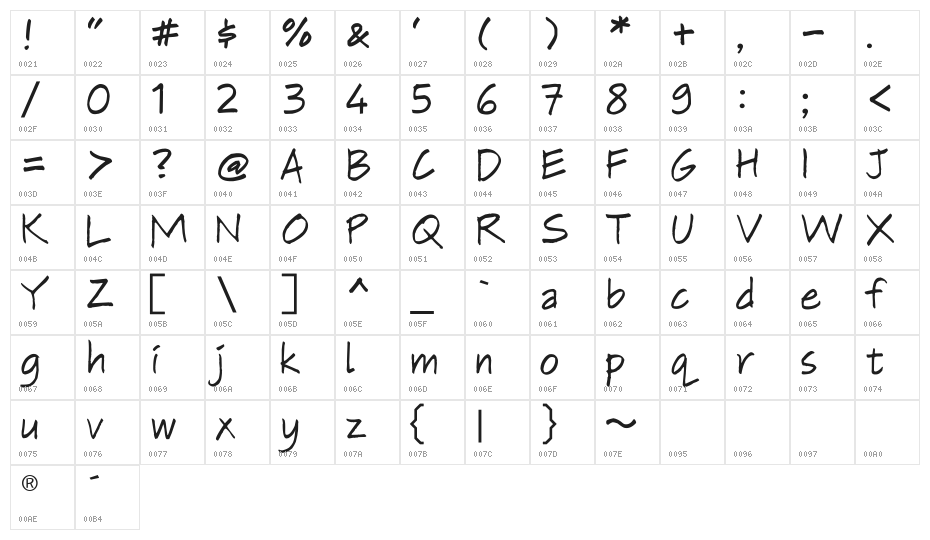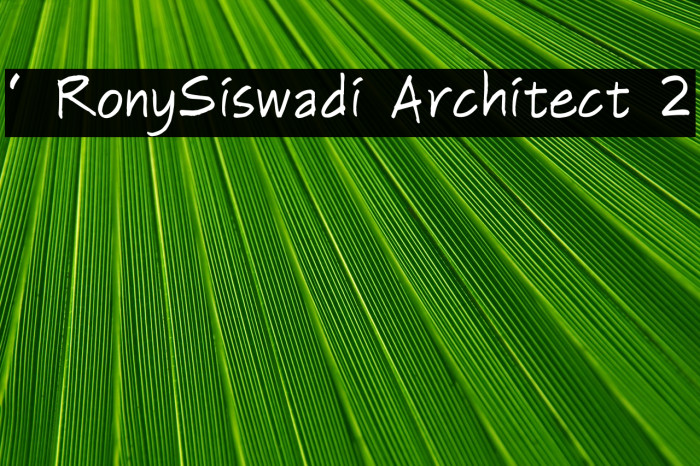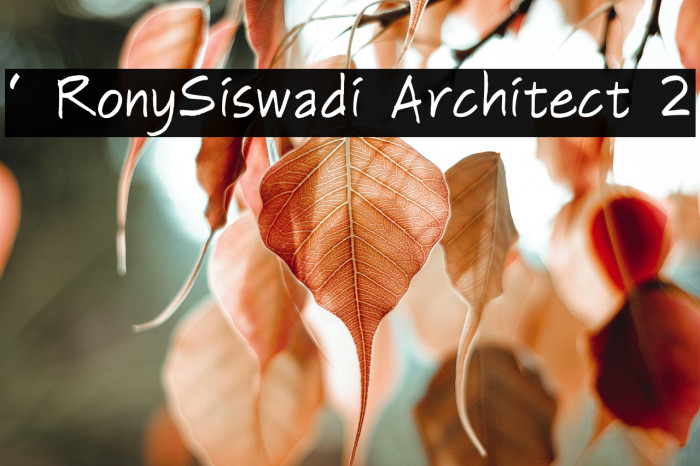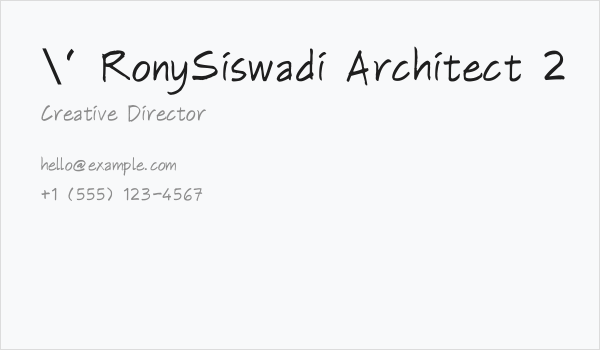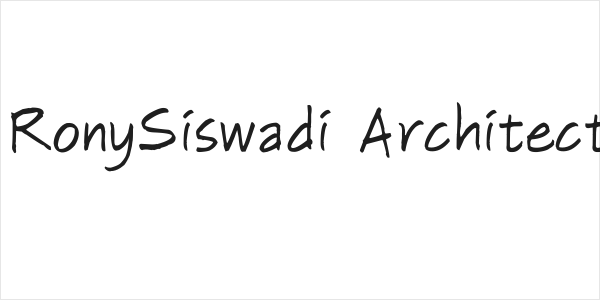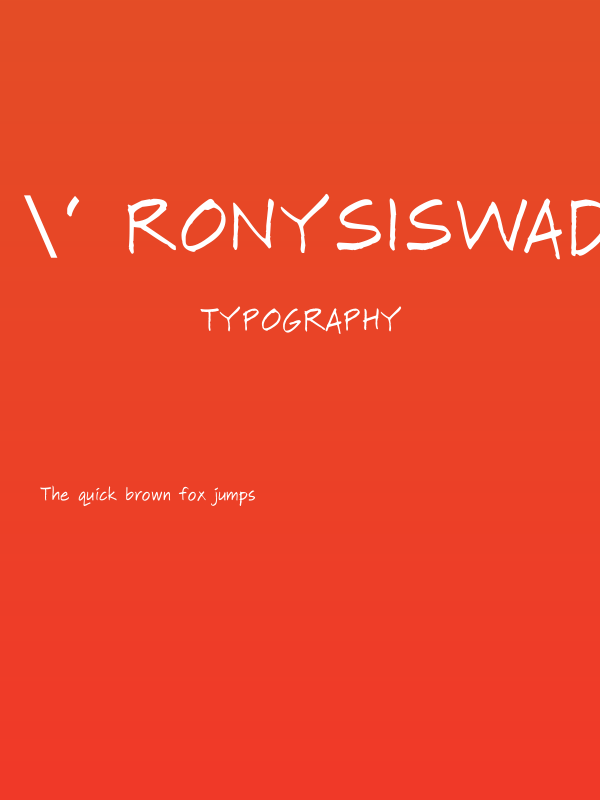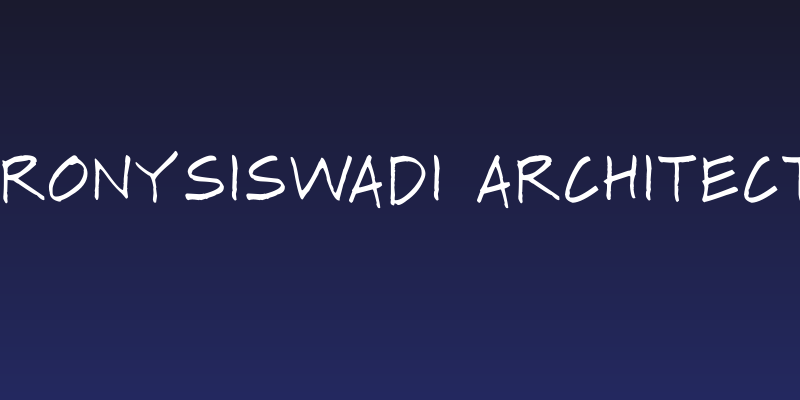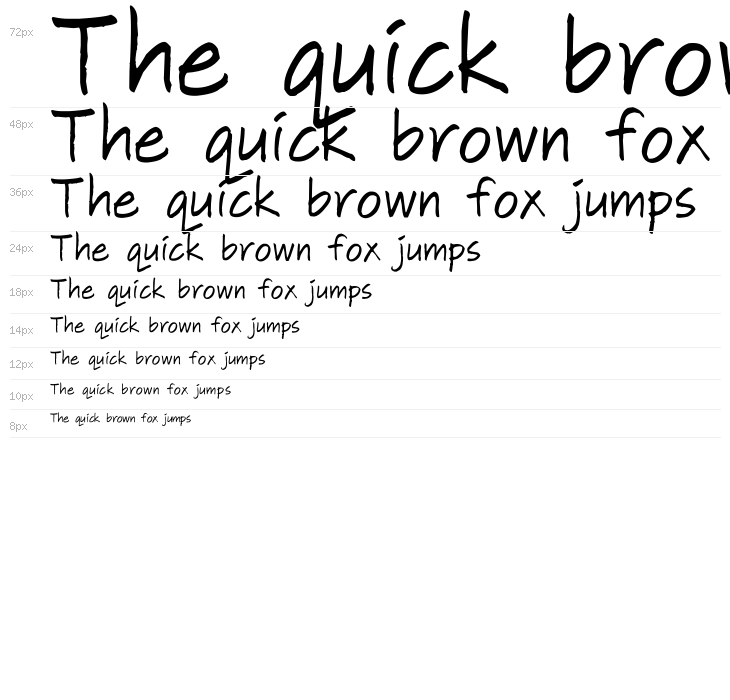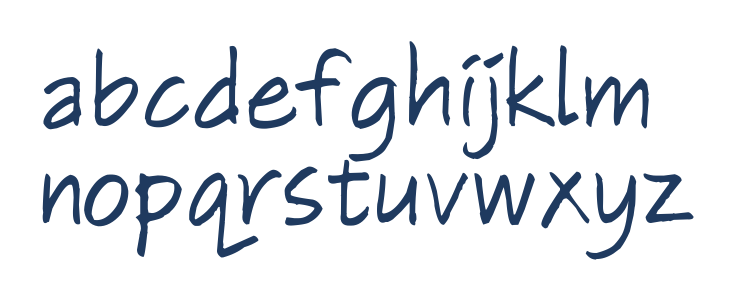
' RonySiswadi Architect 2 Font
| Gesamtstil | Casual, Handwritten |
| Anwendungsfall | Logos, Informal communication, Creative projects |
| Vorgeschlagene Projekte | Ideal for personal branding, creative projects, informal communication, and architectural sketches. |